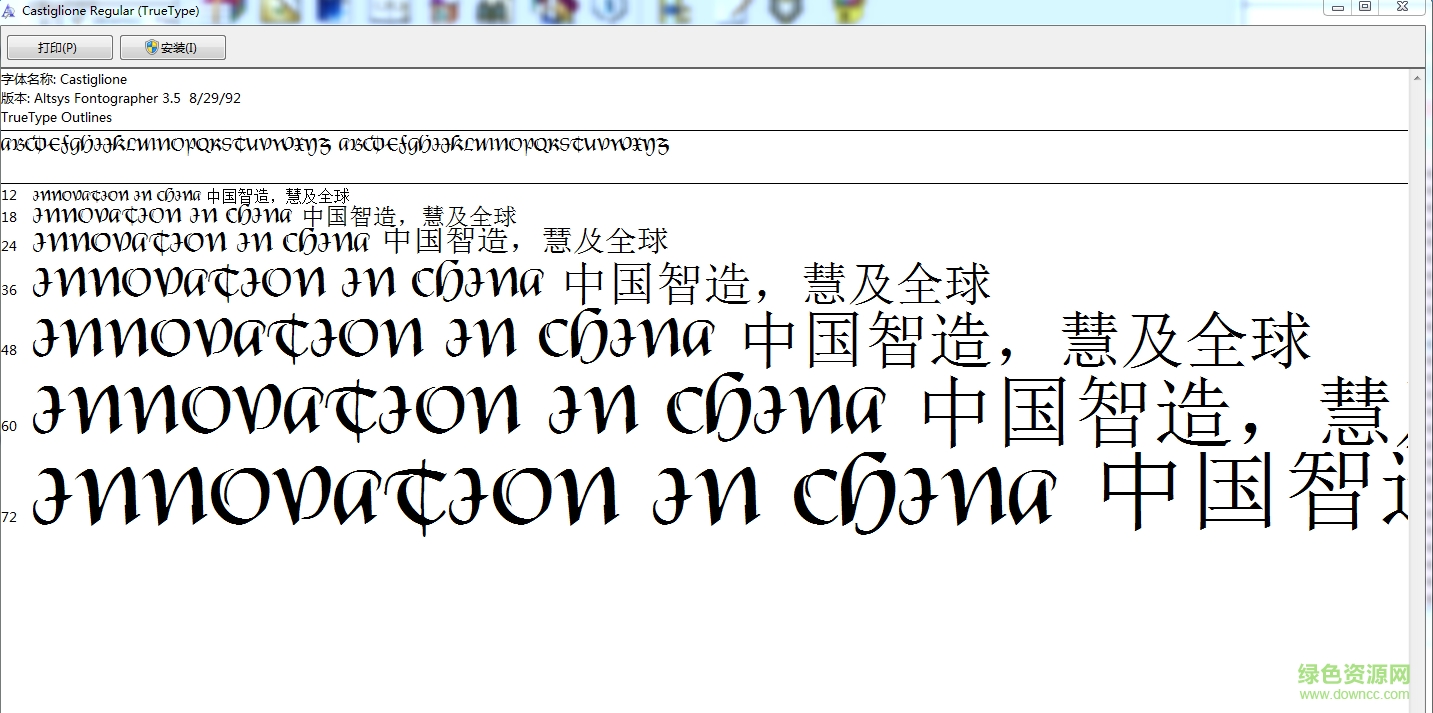
Castiglione字體是一款阿爾及利亞英文字體軟件,阿爾及利亞的文字給人非常耐看的感覺(jué),深受廣大書(shū)法家和年輕人的喜愛(ài),還有更多好看字體盡情期待,歡迎到綠色資源網(wǎng)下載體驗(yàn)!
Castiglione是一款阿爾及利亞英文字體,字體效果比較有趣,喜歡英文體字的朋友可以下載使用看看效果如何。